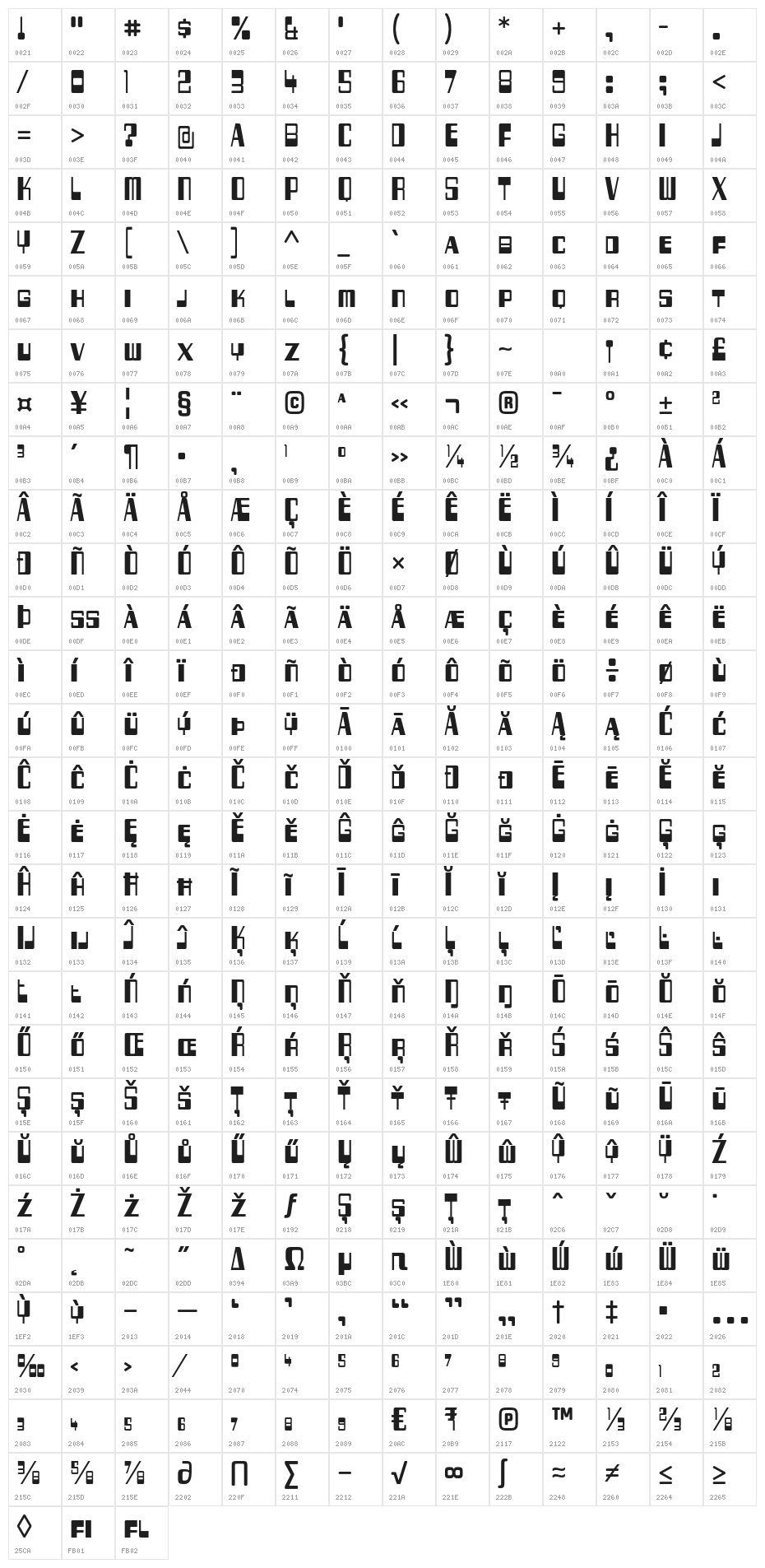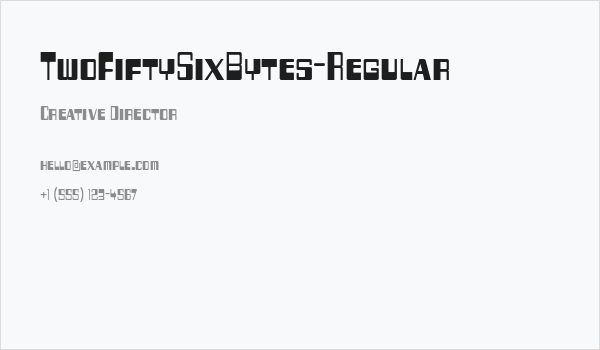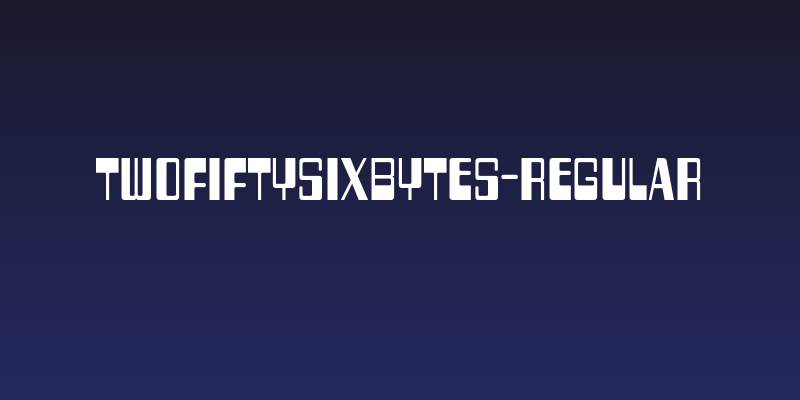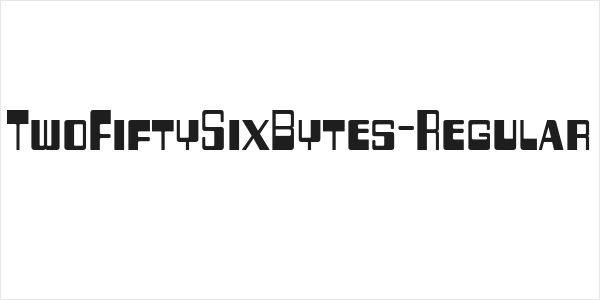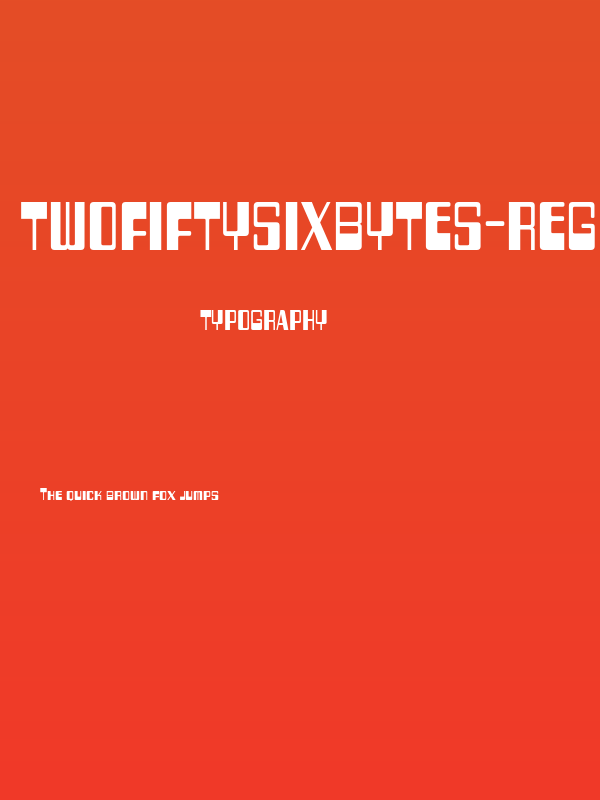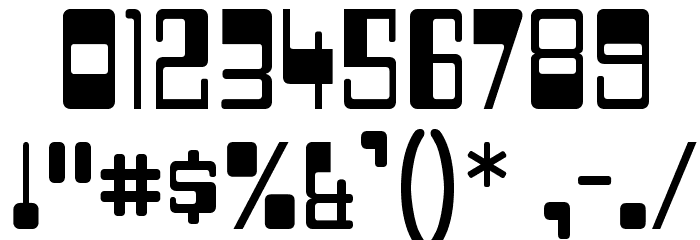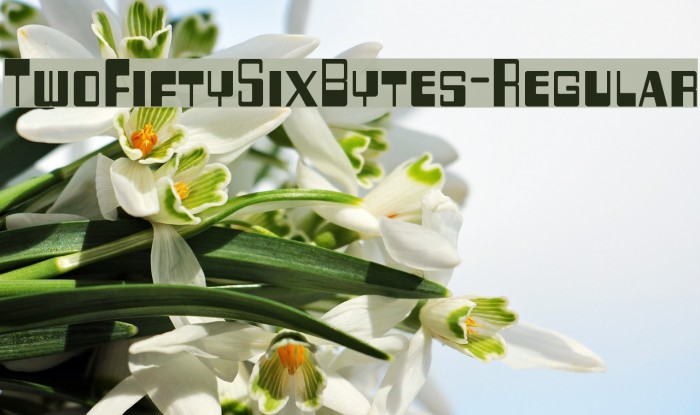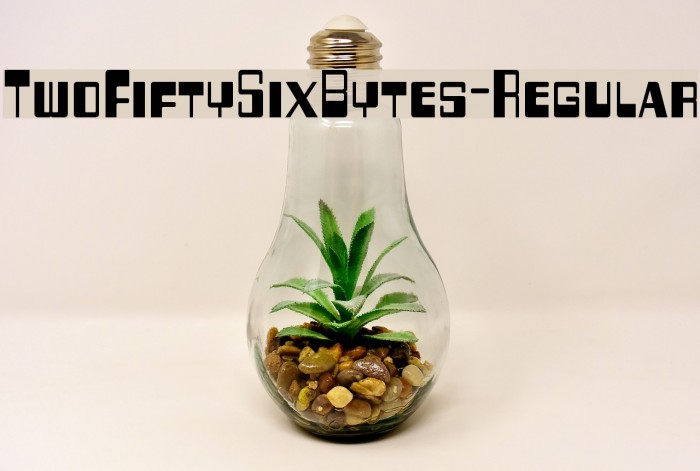
TwoFiftySixBytes-Regular Font
✎ Pixel
| おすすめプロジェクト | Ideal for tech-related branding, video game graphics, digital art projects, and retro-themed designs. |